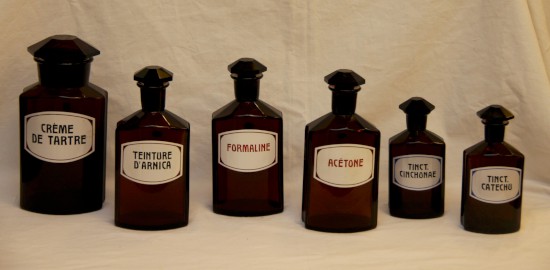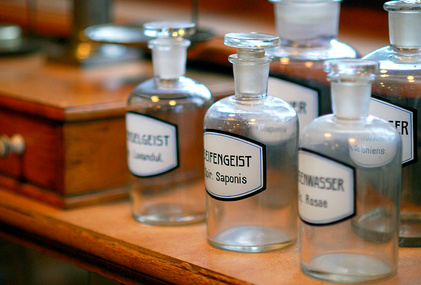
Schrift für alte Chemie/Apotheken Glasflaschen
ich suche eine Schrift für alte Chemie/Apotheken Glasflaschen. 2 Beispiele hab ich mal angehängt, die Schrift ist eigentlich sehr markant. Weiß jemand welche Schrift das ist?
Alternative Vorschläge würde ich auch nehmen :)
Unser Apotheker hat handschriftlich beschriftete Flaschen mit der Apotheke vom Vorgänger übernommen. Und die Chemiker bei mir in der Schule und die, die ich in der Uni kenne, beschriften ihre Flaschen auch selbst.
Die von Dir gezeigten Beispiele sind Art Deco oder Jugendstilschriften. Schau Dich einfach hier mal um: https://www.myfonts.com/search/jugendstil/fonts/
Hier sind auch ein paar Beispiele: http://www.typografie.info/3/page/Schriften/listen.html/_/1900-bis-1909-r44
Die Schrift hat m.E. eine gewisse Ähnlichkeit mit der Benguiat Gothic. Allerdings ist diese keine echte Jugendstil-Schrift sie entstand in den 70er Jahren, ist also viel jünger als es die Apothekenflaschen wohl sind. Als Ersatzschrift würde ich sie nicht unbedingt verwenden, da sie sehr häufig verwendet wird, z.B. gerne im Zusammenhang mit Modethemen oder auch freiverkäuflichen Medikamenten.
Mir scheint es hier eher eine Verwandschaft zu den Anthroposophen-Schriften als zu den vorgeschlagenen »echten« Jugendstilschriften zu geben, wenn ich mir z. B. S, M und A ansehe. Vielleicht findet man bei den Freefonts von Lutz Baar etwas, was dem Charakter entspricht. Benguiat und Herkules passen zwar vom Zeitraum her, aber der Charakter ist doch sehr anders. Da ist ja die FF Liant noch näher dran. Gibt es vielleicht noch Bilder in höherer Auflösung und besserer Schärfe und Perspektive?
Danke schon mal für Eure Antworten. Tut mir Leid wegen der Auflösung da hab ich irgendwie gepennt. Hier ist noch ein Beispiel.
Es war ja schon einiges dabei was dem ähnelt. Allerdings finde ich dass die Jugendstilschriften schon fast zu "modern" aussehen. Ich bin mir relativ sicher die Schrift auch schon mal irgendwo gesehen zu haben, da sie ja schon recht markant ist. Allerdings kann es gut sein, dass dies auf eben solchen alten Flaschen war die mir schon des öfteren begegnet sind. Das heißt aber auch, dass sie häufiger für solche Gläser verwendet wurde.
@Pachulke die Schrift erst zu bauen wäre wohl zu aufwendig. Die Vorlagen sind ja qualitativ nicht so der Hit und unvollständig (JKQVWZ sowie Zahlen fehlen).
Allerdings finde ich dass die Jugendstilschriften schon fast zu "modern" aussehen.
Die sind nicht moderner, sondern modischer. Die gesuchte Schrift hat die Jugendstil-Formensprache ja sehr schön abstrahiert und der Grotesk anverwandelt, eigentlich ist sie also sogar moderner als die hier gezeigten Jugendstil-Beispiele.
die Schrift erst zu bauen wäre wohl zu aufwendig. Die Vorlagen sind ja qualitativ nicht so der Hit und unvollständig (JKQVWZ sowie Zahlen fehlen).
Da kennst Du Catfonts noch nicht. Wenn der nicht gerade mit Linzer Straßenschildern beschäftigt wäre …
Die Zahlen mus ich bei den Linzer Straßenschildern, bei denen ich allerdings noch auf die Vorlagen wartem ja wohl auch neu erfinden.
Diese hatte auch nur so ungefähr 6 unterschiedliche Glyphen
(War übrigens auch eine Anfrage hier im Forum)
Auch mit nur wenigen Glyphen als  Vorlage:
Hardman (nur das Wort),
Kleinsemmering Hofstätten,
Elbtunnel,
Immermann (nur das Wort),
Kanalisirung (auch ein Foren-inspiriertes-Projekt)
Kaufhalle (nur das Wort),
Luxembourg (Ähnlich den Apothekenflaschen von einem Küchen-Zutaten-Sortiments-Regal),
Maass Slicer (nur 3 Vorlage-Glyphen M A und S)
Midroba (nur das Wort Mitropa),
Postamt (nur das Wort),,
Spartakus (nur das Wort Spar),
War ja nicht zu ahnen, dass hier jemand aus 3 Buchstaben gleich ne ganze Schrift zaubert: Nette Leistung ;)